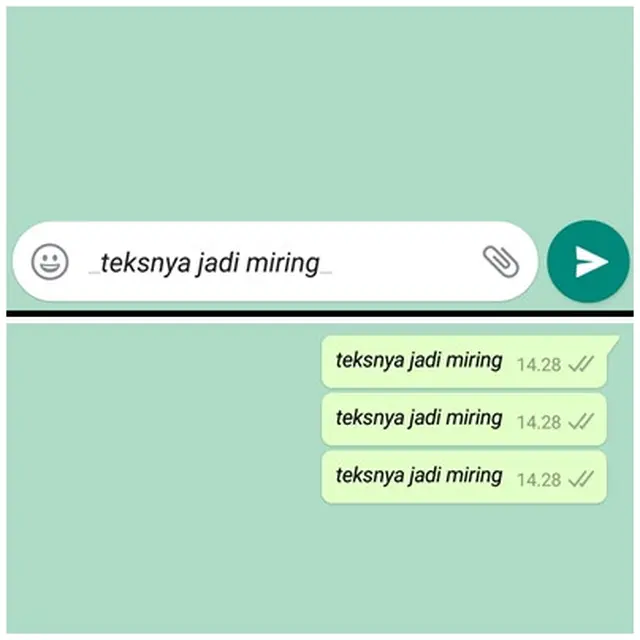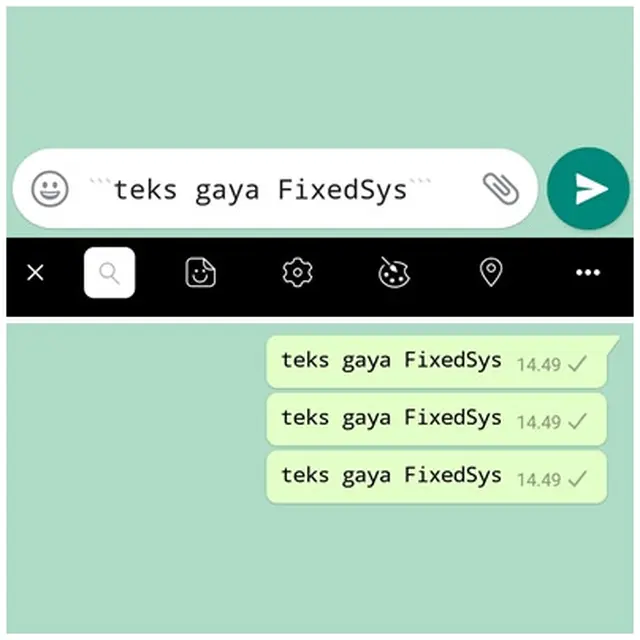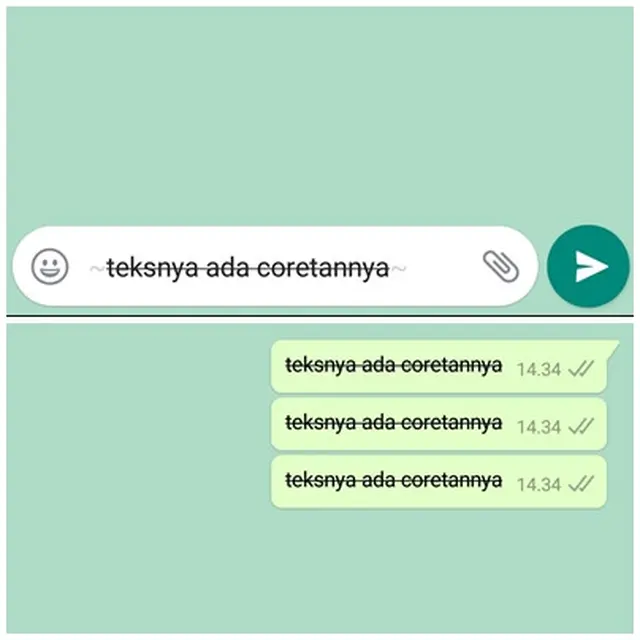
Sebagai aplikasi yang berfokus untuk mengirim pesan atau teks, WhatsApp kerap memperhatikan bentuk teks atau font. Ya, setelah menghadirkan teks tebal miring (bold and italic), kini pengguna WhatsApp bisa menggunakan aneka gaya teks atau font lainnya yang keren.
Agar komunikasi dengan berkirim pesan jadi semakin seru dan atraktif, kamu bisa coba aneka gaya teks ini. Berikut ini Liputan6.com telah merangkum dari berbagai sumber beberapa bentuk atau gaya teks yang bisa kamu gunakan untuk berkirim pesan di WhatsApp, Kamis (4/7/2019).
Teks Miring atau Italic
Bila kamu ingin mengubah teks menjadi miring, maka kamu bisa menggunakan cara mengganti teks WhatsApp dengan cara ini.
Kamu hanya perlu menambahkan underscore “_” di awal dan akhir kata atau kalimat yang mau kamu kirimkan.
Teks Menjadi Tebal atau Bold
Kalau ini membuat teks menjadi tebal alias bold. Caranyapun mudah banget.
Kamu hanya perlu menambahkan tanda bintang “*” di awal dan akhir kata atau kalimat.
Teks Menjadi Tercoret
Nah, untuk gaya teks yang kamu hanya perlu menambahkan garis melengkung “~” di awal dan akhir kata atau kalimat.
Teks Menjadi Miring, Tebal, dan Tercoret
Kalau cara ini merupakan gabungan dari ketiganya. Enggak ribet.
Kamu hanya perlu menambahkan ketiga simbol di atas tadi. Simbol juga bisa diacak alias tidak berurutan.
Maksudnya seperti ini _,~, dan * urutannya bisa diacak dengan catatan penempatan simbolnya secara proporsi. Bila bintang di awal pada posisi pertama, maka di akhir juga meletakkan tanda bintangnya.
Teks Menjadi Bentuk Font FixedSys
Kalau gaya teks di atas biasanya hanya bisa digunakan untuk beberapa momen berkirim pesan saja. Nah, dengan gaya atau jenis teks yang satu ini, kamu bisa melakukannya untuk setiap waktu atau berbagai momen chatting.
Cara menggunakan gaya teks menjadi seperti font FixesSys adalah cukup dengan menggunakan tiga tanda petik miring “```” di awal dan akhir kata atau kalimat. Perlu diketahui, untuk gaya atau jenis font ini jangan menggunakan tanda petik biasa (‘). Tetapi kamu perlu menggunakan tanda petik miring.
Perlu diketahui, bila kamu ingin menggunakan gaya teks seperti di atas, jangan gunakan spasi setelah tanda. Bila kamu menggunakan spasi setelah tanda, maka efek tidak akan muncul atau tidak berubah.